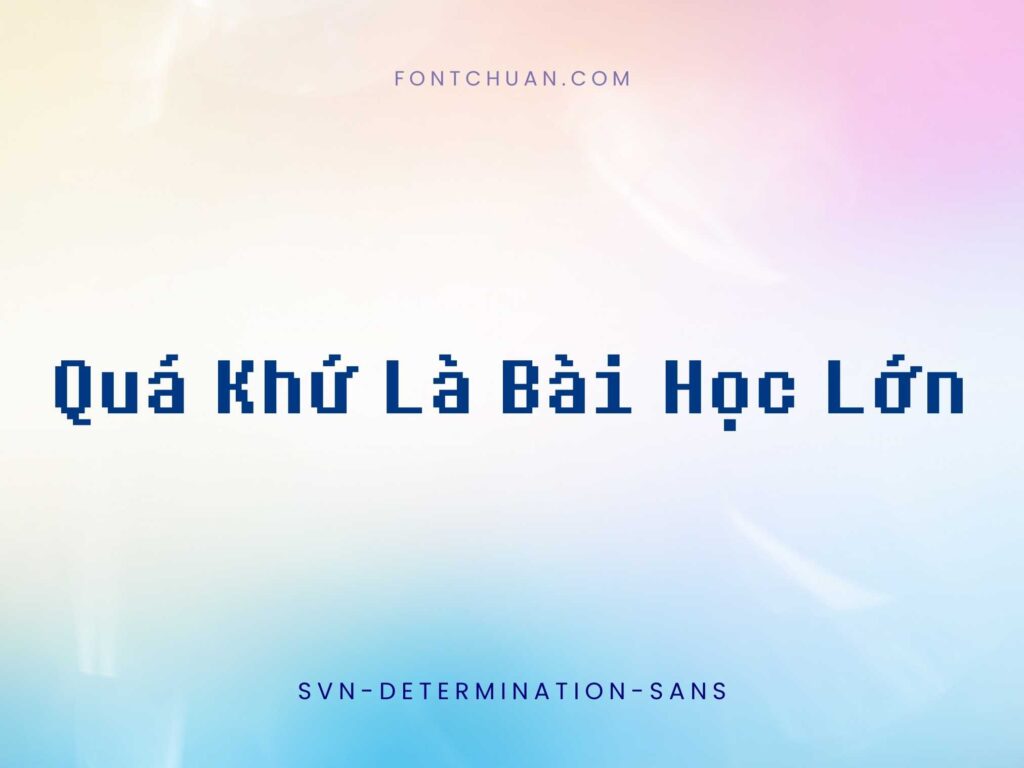
Font SVN Determination Sans Việt Hóa
Tác giả Font: Haley Wakamatsu
SVN-Determination Sans là một font chữ bitmap, pixel được thiết kế bởi Harry Wakamatsu, lấy cảm hứng từ trò chơi điện tử Undertale. Font này có kiểu chữ đậm, dạng pixel, phù hợp cho các dự án thiết kế liên quan đến trò chơi điện tử hoặc phong cách retro. Font đã được Việt hóa để hỗ trợ tiếng Việt bởi Styleno.1 Fonts, đồng thời hỗ trợ nhiều ngôn ngữ khác, giúp mở rộng phạm vi sử dụng trên toàn cầu. Font này được chia sẻ miễn phí cho mọi mục đích sử dụng trên trang Styleno.1 Fonts, đáp ứng nhu cầu của người dùng và ứng dụng thực tế vào các dự án thiết kế.
Đặc điểm thiết kế của SVN-Determination Sans bao gồm các ký tự dạng pixel với chiều cao đồng nhất, tạo cảm giác kỹ thuật số và cổ điển. Font này phù hợp cho các ứng dụng như tiêu đề, logo, đồ họa trò chơi và các dự án sáng tạo khác. Các ngành nghề phù hợp bao gồm quảng cáo, nghệ thuật và thiết kế đồ họa.